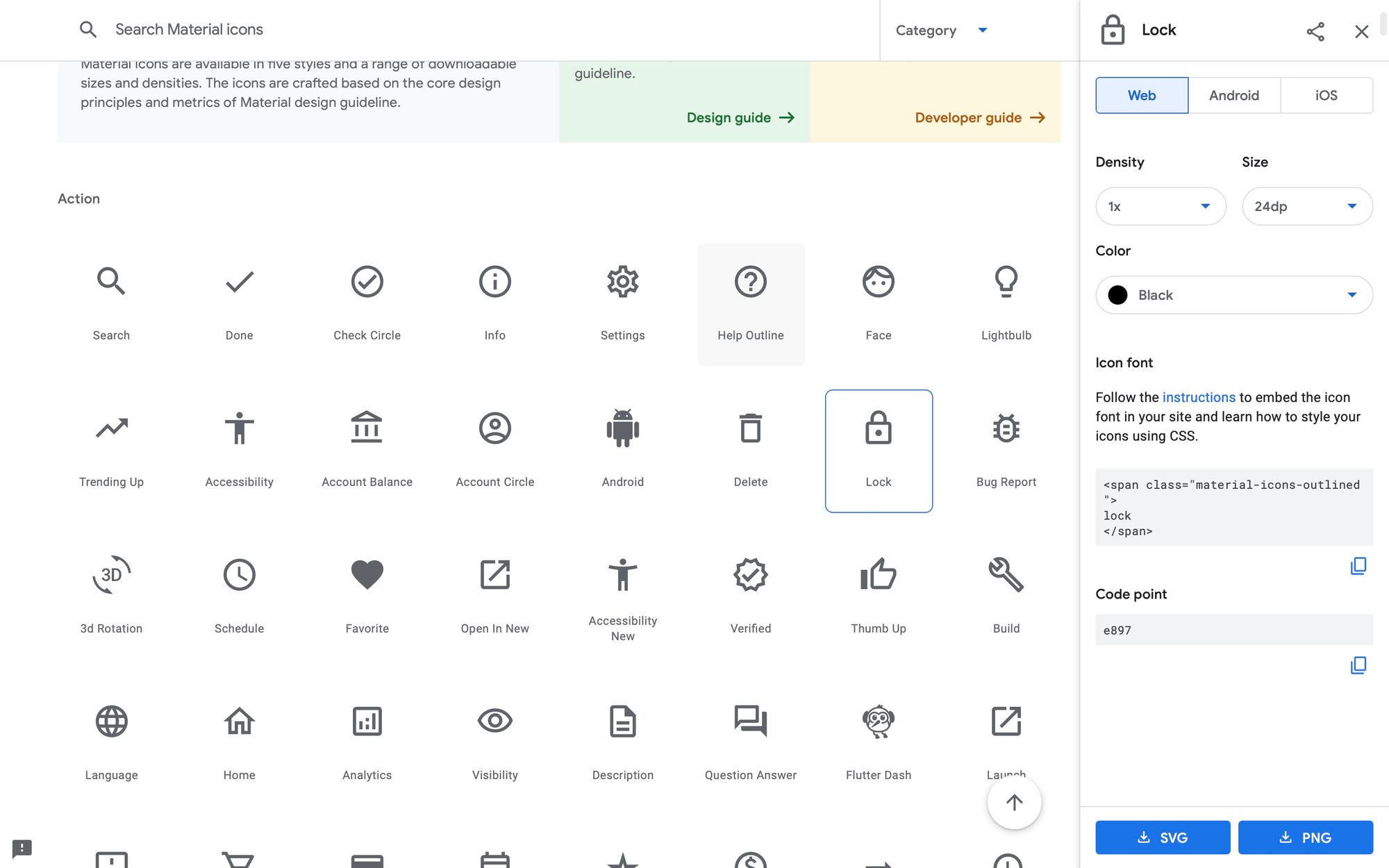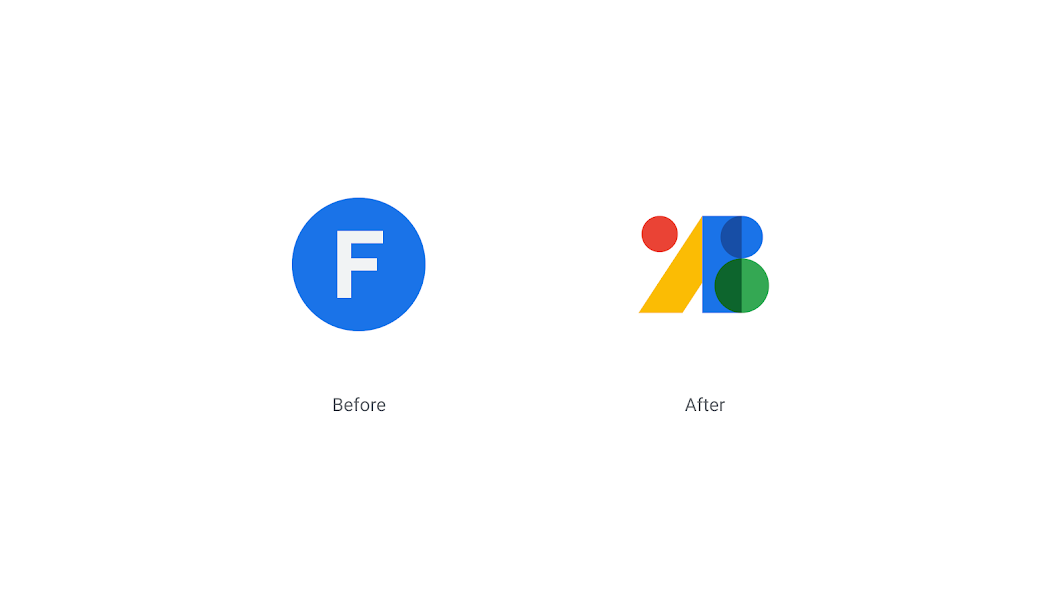
Google Fonts иконки
Google Fonts теперь поддерживает 2000 иконок с открытым исходным кодом, начиная с набора иконок Material Design. Теперь вы можете использовать иконки от Google бесплатно для веб-сайтов и мобильных приложений.
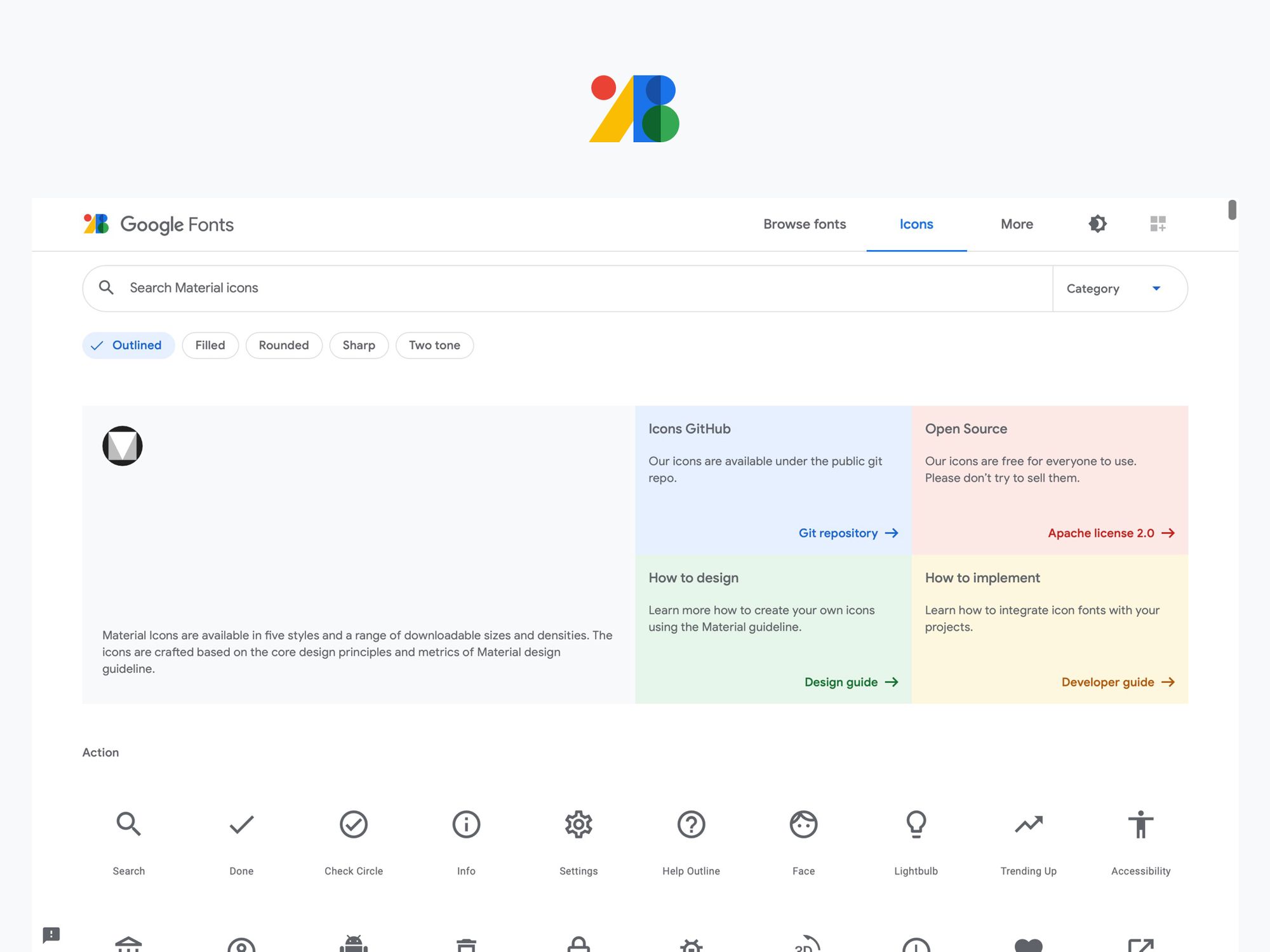
Google Fonts теперь поддерживает иконки с открытым исходным кодом, начиная с набора иконок Material Design.
Поскольку иконография стала центральной частью любой системы дизайна, Material Design поддерживает набор из более чем 2000 различных иконок, доступных в пяти стилях. А поскольку типографика и иконография так тесно связаны, Google теперь добавляет иконки в Google Fonts на fonts.google.com/icons .
"Иконки в материальном дизайне - это восхитительные, красиво оформленные базовые иконки, доступные в различных стилях (Outlined, Filled, Rounded, Sharp, Two tone). И они доступны для загрузки или использования в качестве веб-шрифта через наш API.
Мы считаем, что каждый должен иметь доступ к качественным ресурсам для проектирования, поэтому иконки материалов имеют открытый исходный код и доступны по лицензии Apache 2.0. Мы также планируем добавить другие избранные наборы значков с открытым исходным кодом в Google Fonts в будущем.
Чтобы отпраздновать эту веху, мы также создали совершенно новый значок для самого Google Fonts. Мы решили ребрендировать нашу монограмму «F» и превратить ее в нечто новое, отражающее суть продуктов и услуг, предлагаемых Google Fonts.
На первый взгляд новый логотип может показаться абстрактными формами, состоящими из кругов и прямоугольников, но при более внимательном рассмотрении можно заметить несколько смешанных вместе глифов и иконок. Новый визуальный знак дает нам большую гибкость дизайна, а также дает вдохновение для общего внешнего вида пользовательского интерфейса, чтобы лучше отразить наше видение будущего шрифтов.